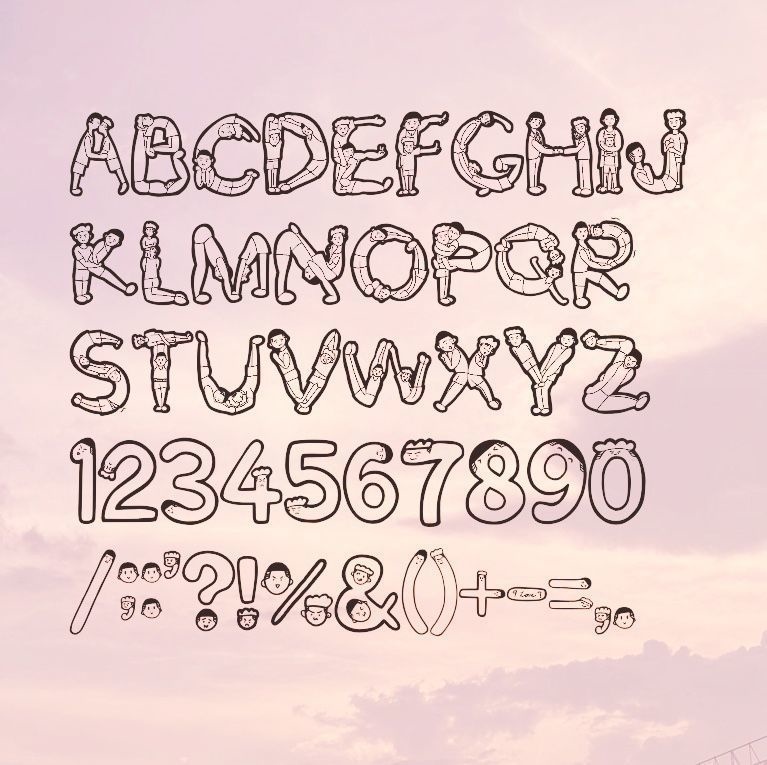
SWRY9797 Font
這是澤良主題的字體。 - 請注意人物的骨架及比例完全沒有邏輯可言。 - 內容包括26個大寫英文字母(沒有小寫),數字及部分常用符號 - 可個人使用、可商用。 - 如因使用此字體引起任何問題,本人概不負責。 - 請勿二次發佈、出售圖利。 - 請勿編輯/修改字型檔。 - 請勿用於製作商標。 - 此字體純為個人興趣製作,並非專業出品,字體如有任何不足之處,請多包涵並歡迎隨時反映。 沢リョテーマのフォントです。 - キャラクターの体型や比率に論理性ではありませ。 - 収録英字:(大文字のみ)・数字・一部の記号 - 個人使用は自由ですが商用・同人で使用する場合は自己責任でお願い致します。 - 下記の事項でのご利用は不可とさせていただきます。 1. フォントデータの販売 2. フォントデータの再配布 3. 商標登録 - このフォントは個人的な趣味のために作成したものであり、プロ仕様の製品ではありません。フォントに不備がある場合はご容赦ください。ご意見・ご感想をお気軽にお寄せください。 This is a Sawaryo-themed font. - Please be reminded that there is no logic in the body gesture and proportion of the characters. - Contents: alphabetic characters (uppercase only), numbers, some symbols - The font can be used personally/commercially. - I am not responsible for any problems that may arise from using this font. - Do NOT redistribute/ sell it for profit. - Do NOT edit/ amend the data file of the font. - Do NOT use for design Logo and Trademark registration. - This font was created for personal enjoyment and is not a professional product. Please forgive any imperfections in the font. Please feel free to send us your comments and feedback. 우성태섭 테마의 폰트입니다. - 글자의 형태와 비율에 논리성이 없음을 유의해 주세요. - 내용: 알파벳(대문자만 가능), 숫자, 일부 기호 - 본 폰트는 개인적/상업적 용도로 사용 가능합니다. - 본 폰트 사용으로 인해 발생하는 모든 문제에 대해 책임지지 않습니다. - 재배포/판매를 금지합니다. - 본 폰트의 데이터 파일을 편집/수정하지 마세요. - 디자인, 로고 및 상표 등록 용도로 사용하지 마세요. - 이 글꼴은 개인적인 관심사에 따라 제작되었으며 전문적인 제품이 아닙니다. 글꼴에 미흡한 부분이 있다면 너그럽게 양해해 주시고, 피드백을 남겨주시면 감사하겠습니다. (한국어 설명은 번역자가 작성한 것입니다. 문제가 발생하면 알려주세요. 정말 감사합니다.) 2025.09.07